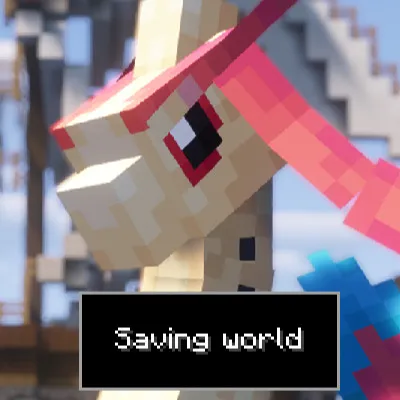
Modern Font Pack добавляет в Minecraft аккуратный современный шрифт, который делает интерфейс, чат и подсказки менее громоздкими и приятнее для глаз.
В паке есть три варианта сглаживания - Basic, HD и Supreme - под низкие, средние и высокие разрешения экрана, а также пять вариантов для CJK-писем (JP, KR, CN, TW, HK), чтобы иероглифы выглядели правильно в вашем регионе. Пак поддерживает эмодзи и множество "фанси" символов, их можно просто вставить в чат без всяких команд типа /tellraw или /title. Шрифты взяты из семейства Noto, поэтому всё выглядит аккуратно и единообразно.
Текстура для интерфейса, делает шрифт современным и более читабельным